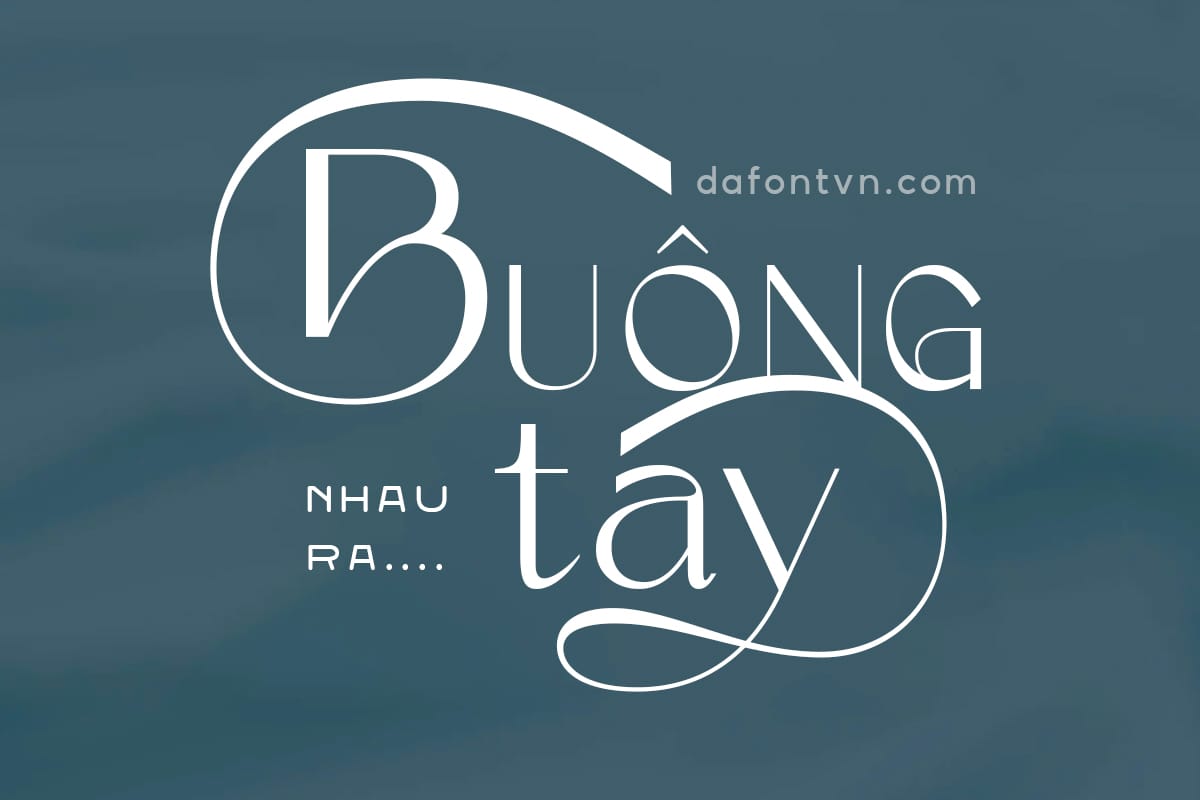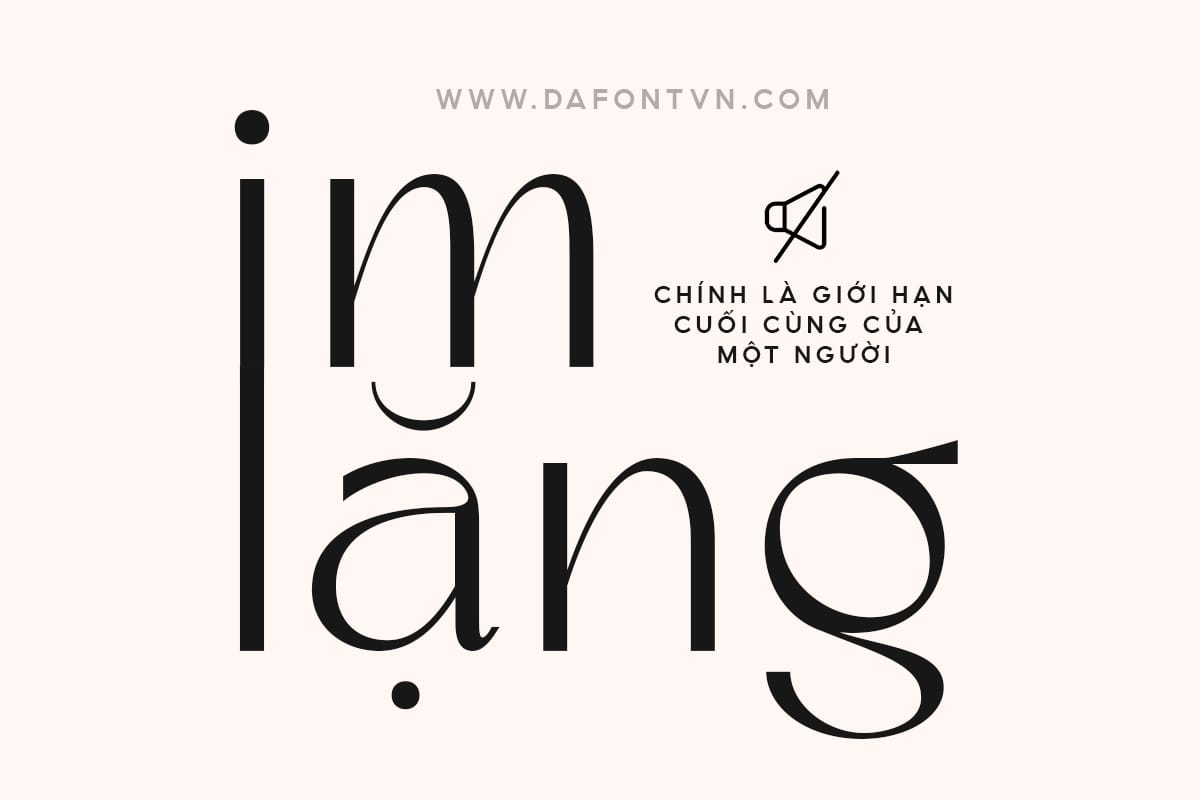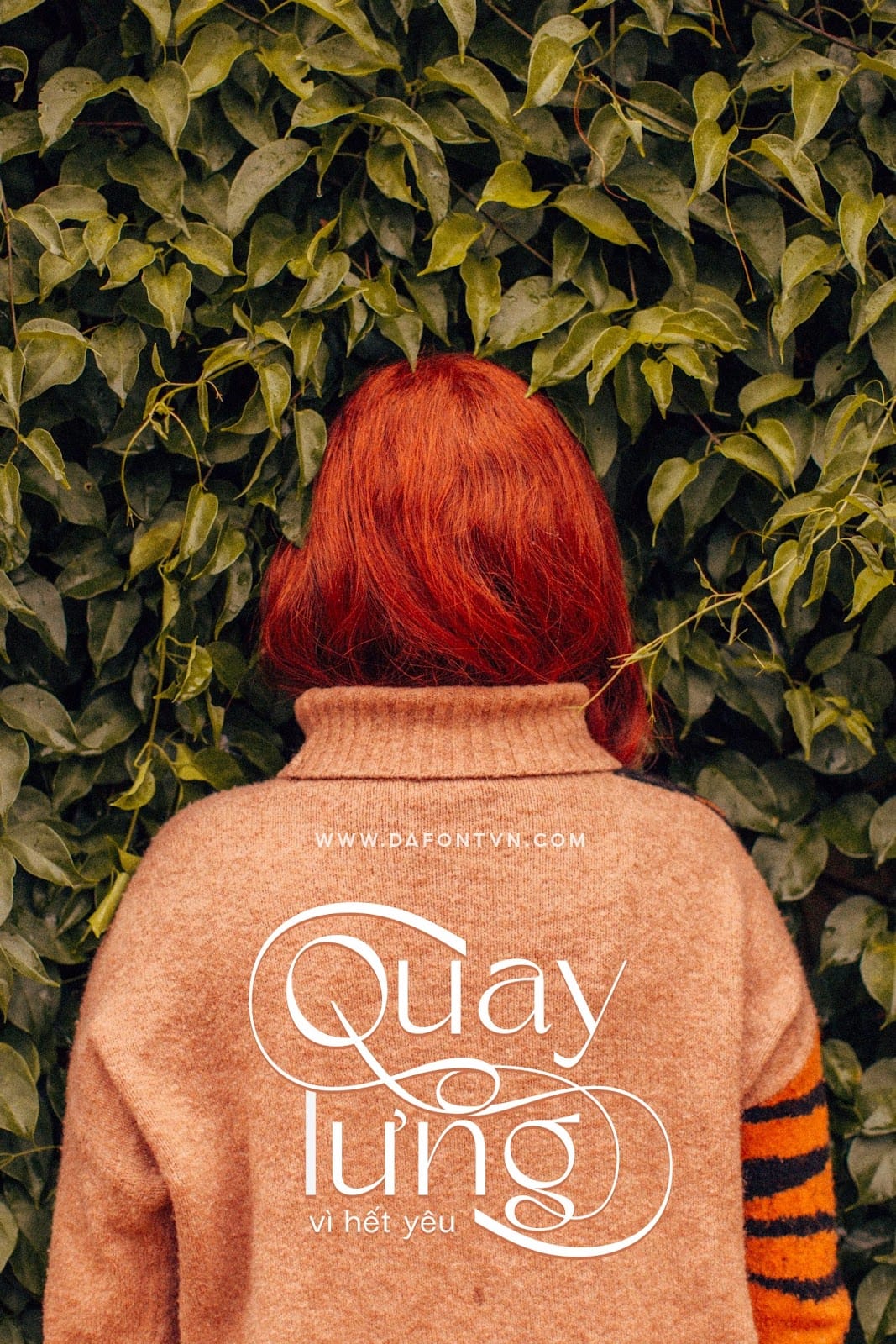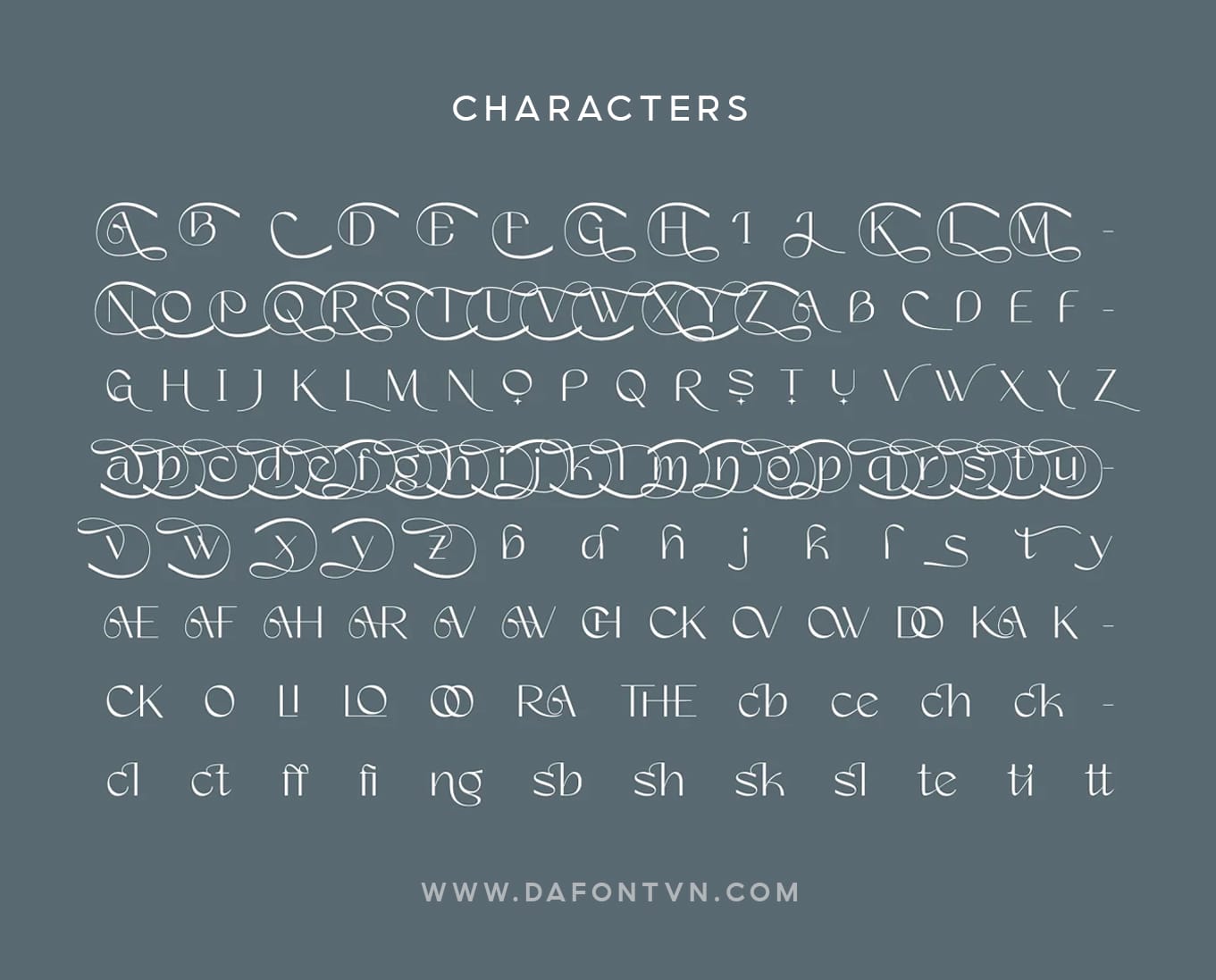
Font Blade Rush Việt hóa – Phông chữ hiện đại
Blade Rush Modern Sans Serif Font là một phông chữ san serif hiện đại mong phong cách độc lạ và bắt mắt với các chữ cái viết hoa và viết thường đi kèm với các glyph uốn lượn siêu đẹp được thiết kế tỉ mỉ. Blade Rush phù hợp cho nhiều thiết kế khác nhau như tạp chí, làm đẹp, thời trang, typography, bìa sách…Font Blade Rush được việt hóa đầy đủ, kerning và đã thay đổi lại một số dấu để phù hợp hơn với font, bạn có thể sử dụng các glyph trên PTS hoặc AI. Ngoài ra các ký tự được mã hóa PUA.